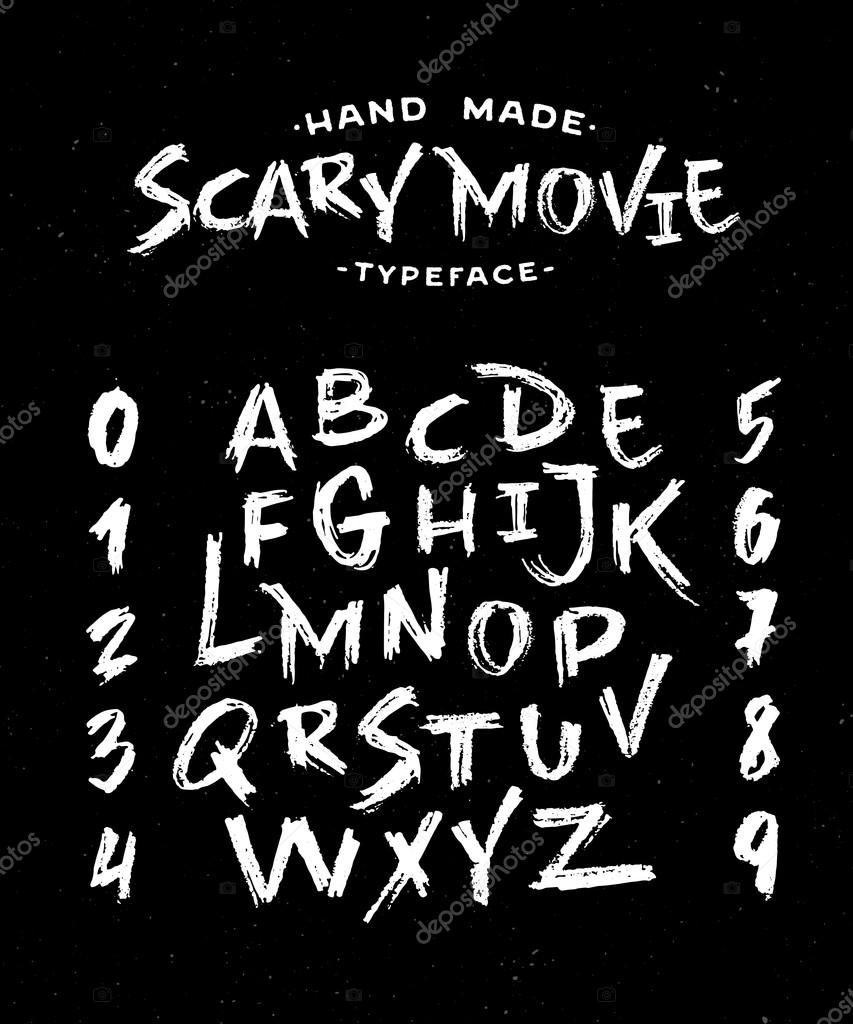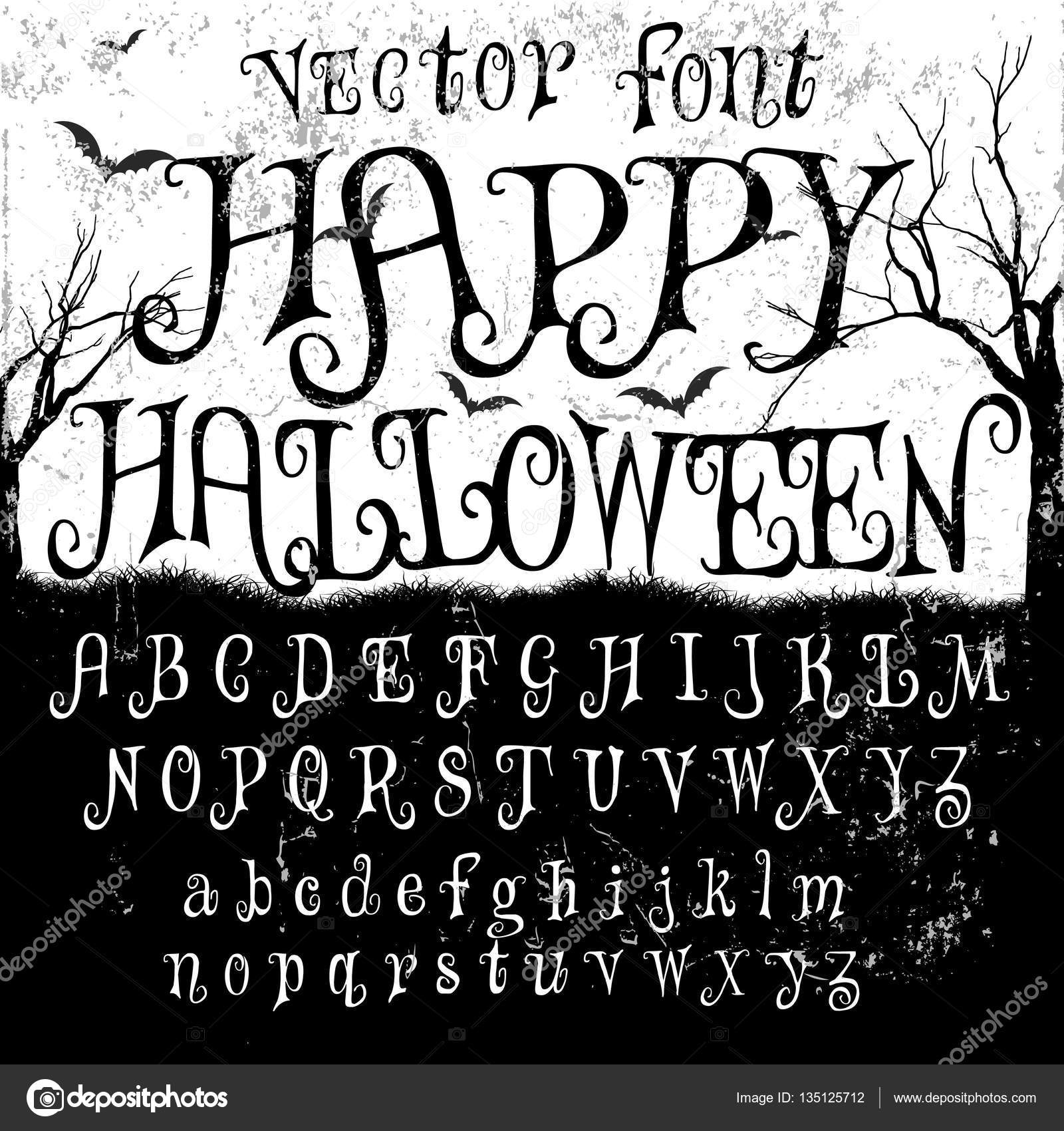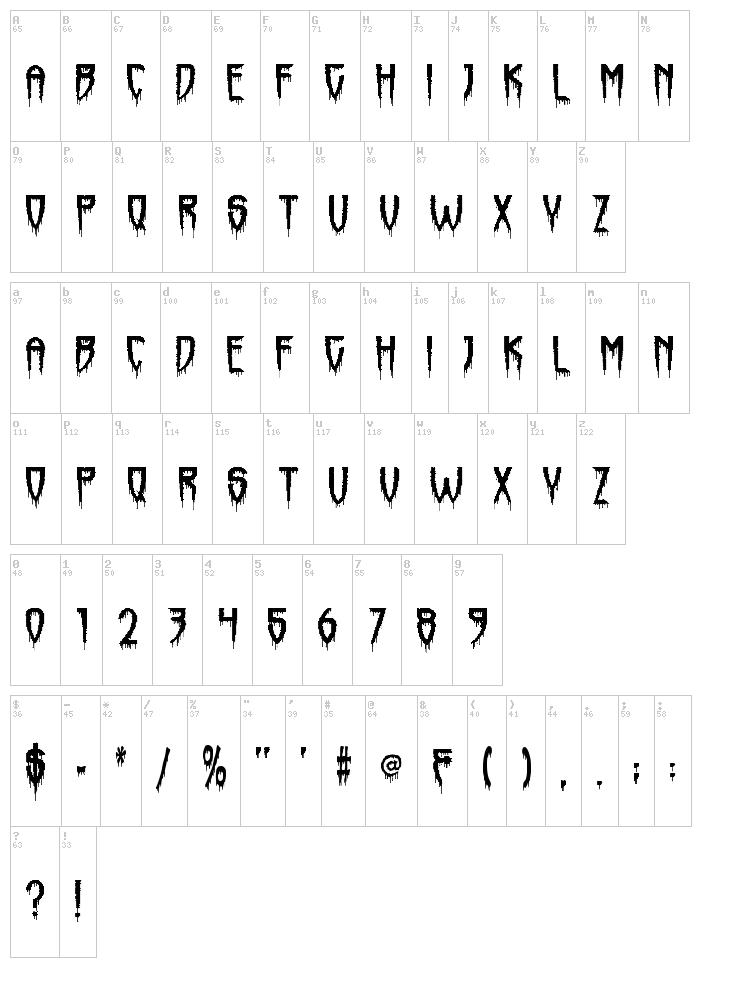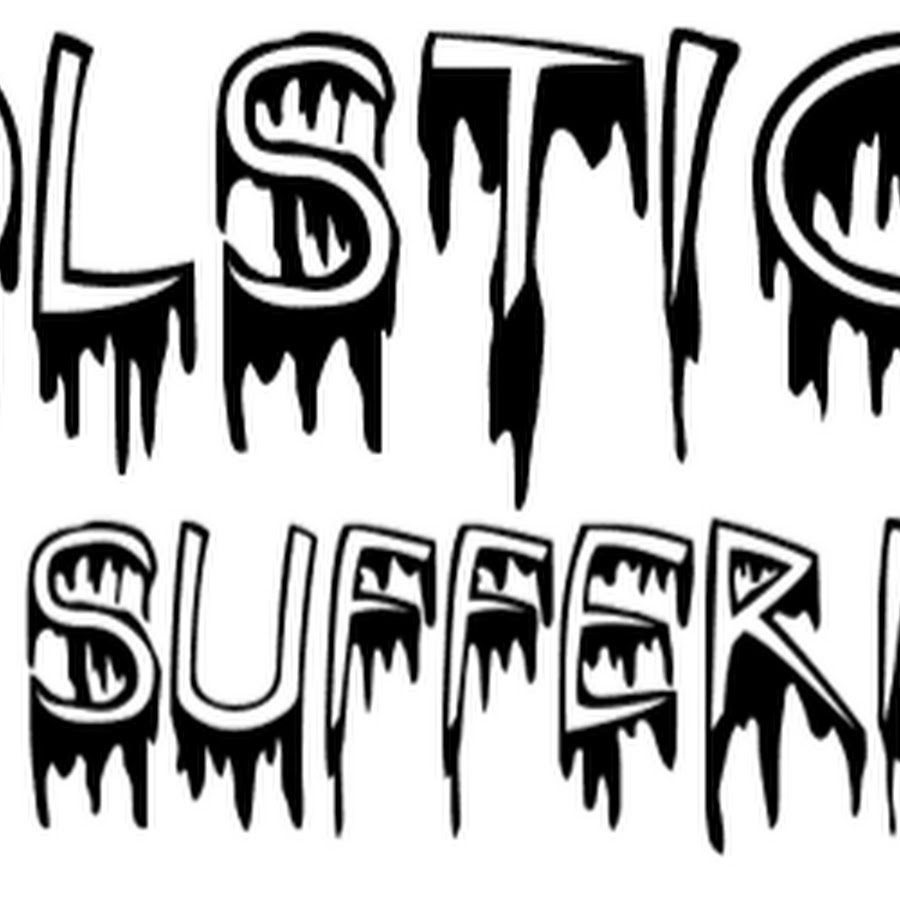
Жуткие буквенные шрифты.
Жуткие буквенные шрифты. Если вам нужно больше альтернатив для декорированного текста, просто нажмите «загрузить больше шрифтов». Альтернативы, которые появляются здесь, более случайны, немного отходят от стандарта и объединяют ресурсы, которые имеют мало общего, смайлики и символы.
Жуткие буквенные шрифты.
Теперь, когда ваш текст сохранен в буфере обмена вашего ПК или телефона, используйте команду вставьте биографию, описание, комментарий или сообщение.
Жуткие буквенные шрифты. Помните, что может быть некоторая несовместимость символов Unicode. Следовательно, убедитесь, что фрагмент отображается так, как ожидалось И если да, отрегулируйте его, чтобы не удивлять своих подписчиков.
Наконец, мы рекомендуем вам выбрать один или два из этих шрифтов для частого использования, чтобы они особенность ваших сообщений.
Поэтому попробуйте использовать шрифты, чтобы улучшить внешний вид субтитров, которые вы пишете для изображений. Помните, что визуальная привлекательность в Интернете очень велика, и использование его в дословной части содержания привлечет больше внимания к вашему сообщению.
И не забывай применить стилизованные надписи в биографии профиля, если вы сочтете это подходящим. Используйте эту функцию, чтобы привлечь тех, кто еще не подписан, а также побудить тех, кто уже подписан на вас, предпринять определенные действия.
Тема для убийства
A Theme for Murder разработан Кристофером Хансеном и является одним из жутких шрифтов в сценарии и каллиграфии. это бесплатно для личного дизайна.
Ведьма Жуткая
The Witch Spooky — шрифт с волшебным и таинственным оттенком.В конце букв волшебный плющ, переходящий в страшную тему. Этот шрифт можно использовать для оформления плакатов, листовок, страшных тем и фильмов на тему Хэллоуина.
Оками